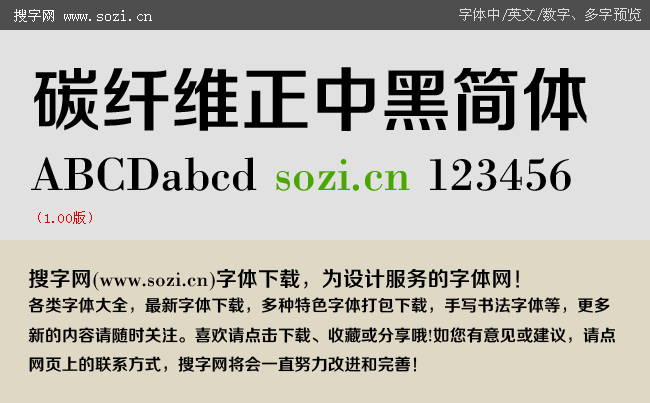
碳纖維正中黑簡體
本字體應開發(fā)者方正字體要求已下架,謝謝您的理解與支持!搜字網(wǎng)提供一碳纖維正中黑簡體中文藝術字體下載,正黑體取傳統(tǒng)黑體結構,筆形全部采用平行、垂直與弧度的流線形設計,簡潔易識、美觀大方,具有個性,加之鏡像對稱的現(xiàn)代構成形式,達到莊重與簡潔有機融合、設計感與閱讀功能兼?zhèn)涞淖罱K效果。適合書籍排版,報紙排版,海報設計,包裝設計等廣告設計場合應用。